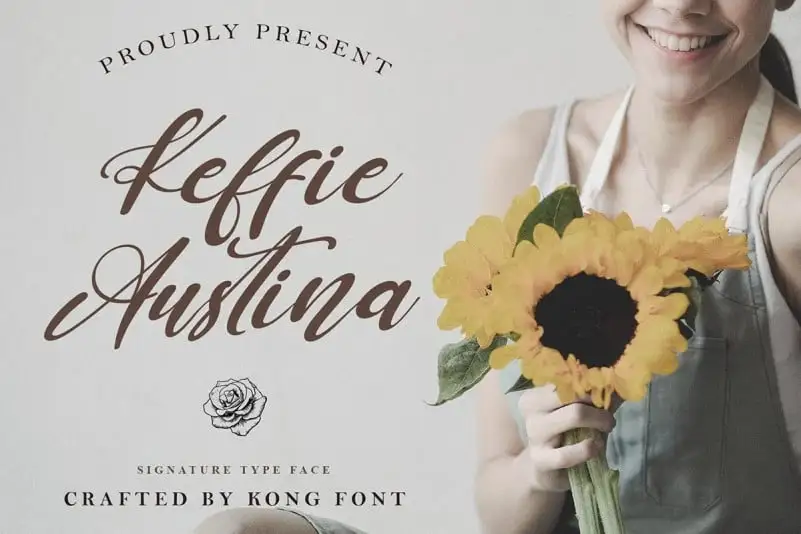
Keffie Austina Script Font – Fonte Grátis
Keffie Austina Script Font
A Keffie Austina Script é uma fonte script que exala elegância e beleza, criada pelo Kong Font. Esta fonte é perfeita para destacar a sua individualidade em qualquer projeto. Composta de um conjunto básico de letras e alternativas, também inclui números, fracionados, símbolos básicos e pontuação, tornando-a uma opção versátil para diversas necessidades de design gráfico. Uma das principais aplicações desta fonte são no desenvolvimento de logotipos, criação de templates, embalagens, blogs, marcação, capas de livros, revistas, anúncios e impressões comerciais. A Keffie Austina Script é uma ótima escolha para quem busca uma solução de fonte elegante que possa ser utilizada tanto em projetos profissionais quanto pessoais. Ela adicionará um toque refinado e único a qualquer projeto, tornando-o mais interessante e memorável.